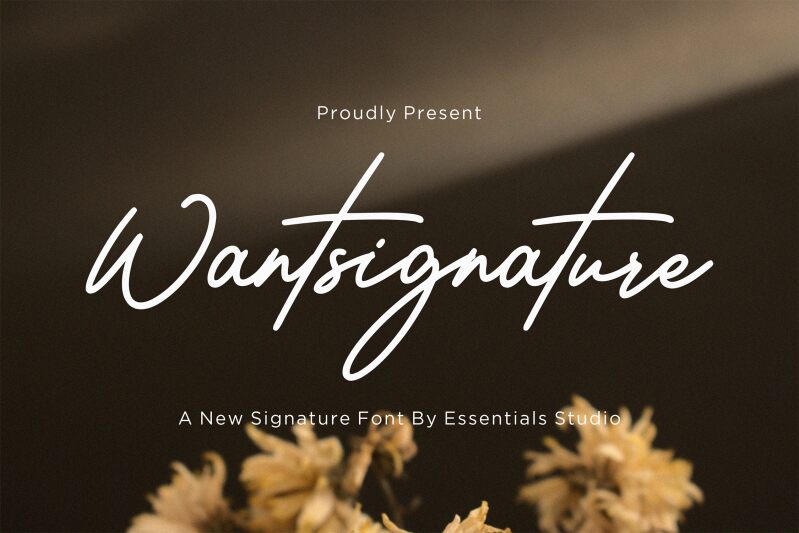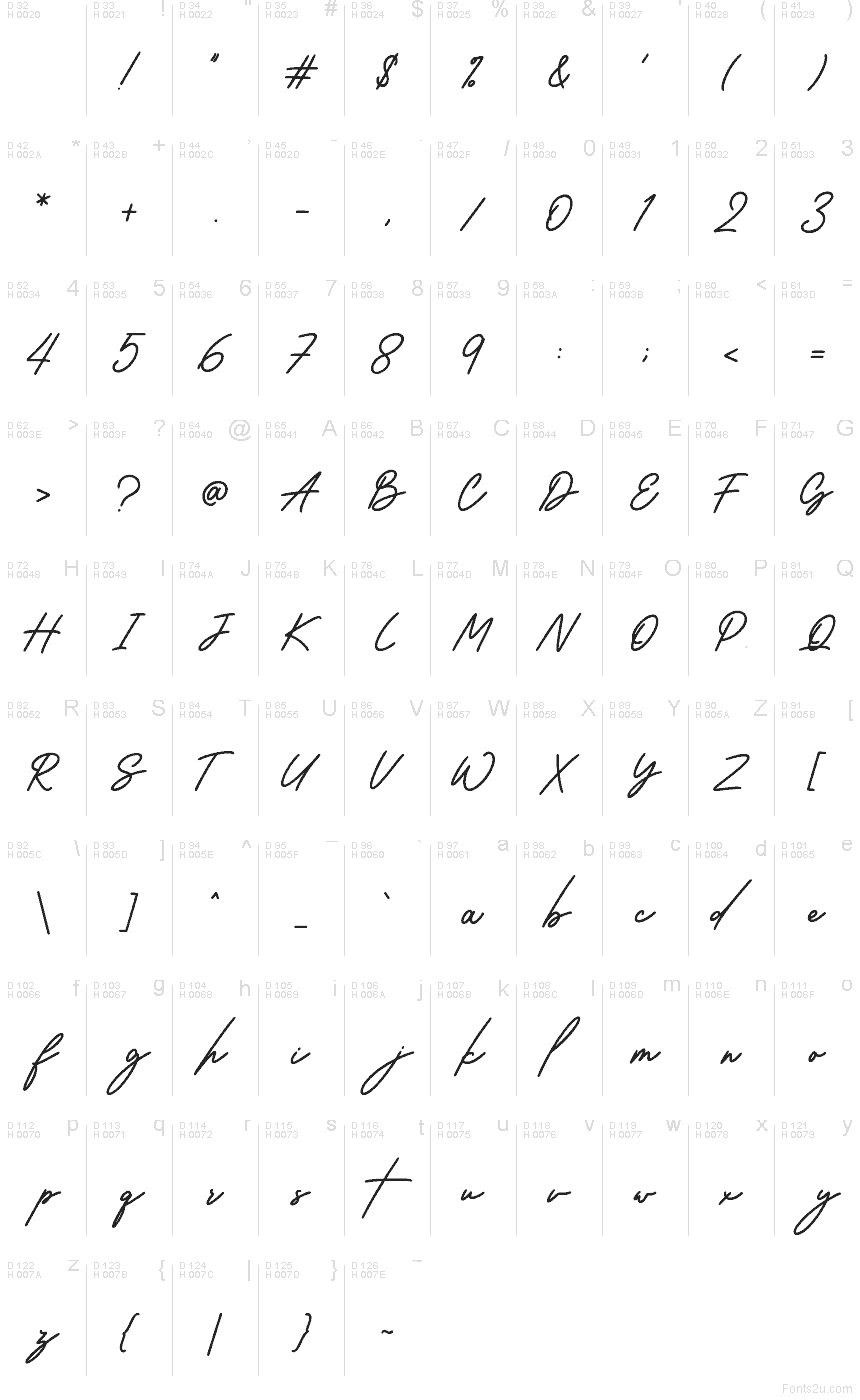
Wantsignature de Essentials Studio es una tipografía manuscrita gratuita con un ritmo rápido y un toque a la moda. Las letras se entrelazan en trazos largos y fluidos, mezclando curvas ligeras con líneas afiladas que le dan a la tipografía un aire de firma personal, lejos del acabado rígido de un pincel.
Encaja perfectamente en branding, packaging de boutiques, gráficos para redes sociales, portadas y papelería de bodas, donde un toque manuscrito relajado ayuda a definir el tono. Como tipografía gratuita, también funciona muy bien en tarjetas de título, bocetos de logotipos y citas cortas, especialmente cuando buscas que un trazo largo o un bucle unifique la composición.